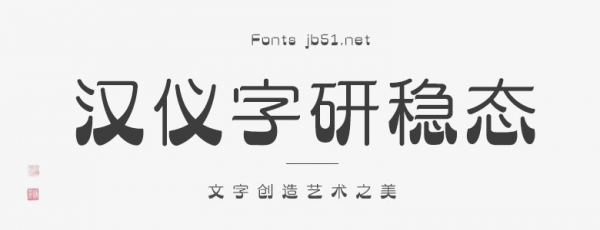
漢儀字研穩(wěn)態(tài)簡(jiǎn)一款書(shū)寫(xiě)很新穎的字體,具有強(qiáng)烈的視覺(jué)沖擊力。適用于海報(bào)、電商海報(bào)設(shè)計(jì)、店鋪設(shè)計(jì)、標(biāo)志設(shè)計(jì)、字體設(shè)計(jì)等領(lǐng)域。